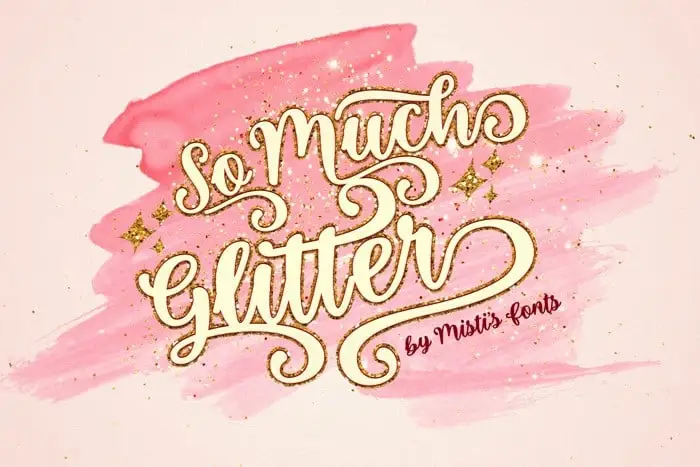
So Much Glitter Script Font – Download Grátis
A ‘So Much Glitter Script Font’ é uma elegante fónt que evoca a arte da escrita à mão, mas mantém um toque contemporâneo e moderno. Criada por Misti’s Fonts, esta tipografia de script é perfeita para aqueles projetos em que você deseja destacar-se do resto da multidão. Possui uma forma brilhante e envolvente, com seus adoráveis “swashes” (cortes) cuidadosamente elaborados. É ideal tanto para criações de logotipo como para postagens de aniversário natalinas ou anúncios publicitários. Seja para festas de casamento ou qualquer outro tipo de projeto visual, a ‘So Much Glitter Script Font’ é uma escolha perfeita que tornará seu trabalho único e memorável.